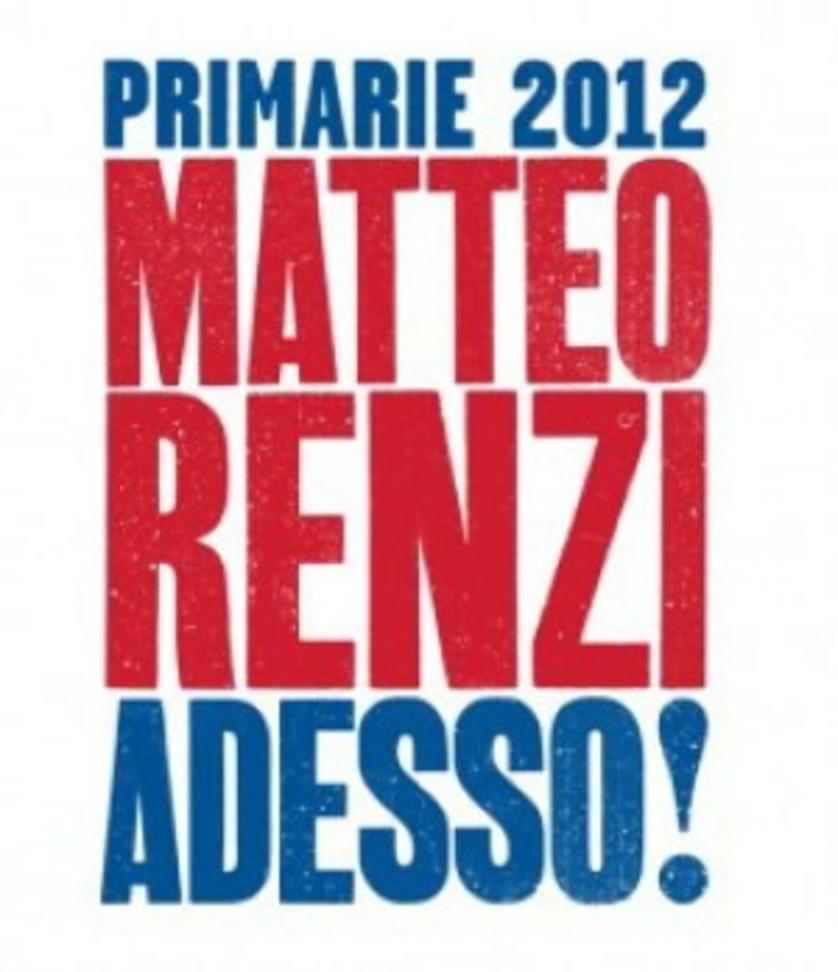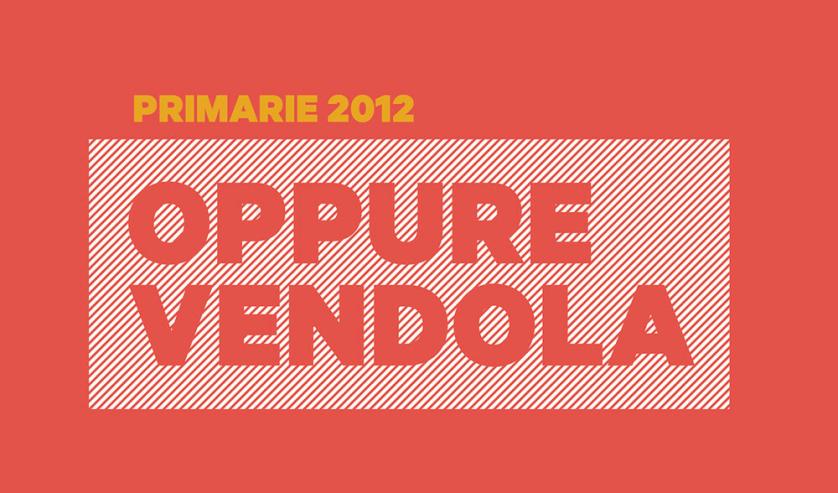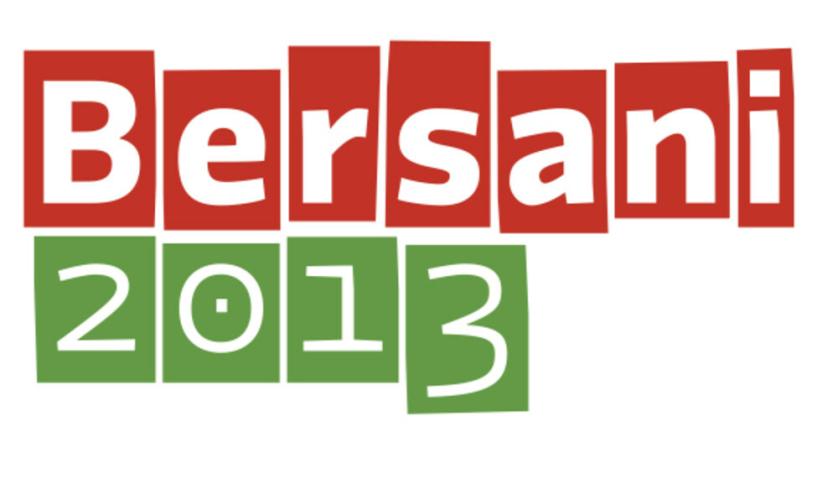
La tipografia delle primarie: JFRenzi, PierLouis e Vendolik
Un anno e mezzo fa, in questa rubrica, scrissi di tipografia e comunicazione politica: Milano ne fu per qualche settimana un pessimo ma interessante esempio.
Poi tutto si appiattì. Il rigore montiano avvolse anche la comunicazione visiva. Per mesi abbiamo visto solamente le identità visive di forum economici in cui la facevano da padrone Monti, Draghi, Baskerville, Caslon e Garamond e Bodoni. Un’Europa finalmente unita.
Ma ora basta. Finalmente ci stiamo avvicinando alle elezioni e le schermaglie tipografiche sono iniziate. Restando Berlusconi ancora al margine della competizione, ci dobbiamo accontentare delle scaramucce a suon di “bastoni” tra i principali candidati alle primarie del Partito Democratico. Ma questa volta si sono impegnati veramente e ci stanno regalando grandi soddisfazioni.
In molti hanno accusato Matteo Renzi di essere “Obamified”. Non sanno invece che il ragazzino terribile, il nuovo che avanza, non è altro che stile vintage. Altro che Obama: le maniche di camicia arrotolate, la riga in parte e il piccolo ciuffetto che sta crescendo completano il kit del giovane democratico che ci salverà. I caratteri che compongono il suo nome e la parola d’ordine “Adesso!” sono condensati e molto grossi. Derivano, nel disegno, da quelli di legno che si usavano per comporre i manifesti due secoli fa, di ispirazione nordamericana. Un po’ come l’Impact berlusconian-leghista di cui scrissi su questo sito. Ma soprattutto composti in quel blu e rosso da convention americana, non possono non ricordarci le campagne democratiche degli anni sessanta. Soprattutto quella di JFK.
Perciò, “Fuori dal Vietnam, ADESSO! Tutti alle Cayman!”.
Il problema (di questi tempi lo è) potrebbe essere ricordare invece la campagna molto simile di Richard (Dick) Nixon. Ma soprattutto se l’avversario per lui sarà Berlusconi (notizia di oggi ci rassicura di no) potrà riciclare uno dei più famosi slogan non ufficiali di quella campagna: “THEY CAN’T LICK OUR DICK”. Il carattere e i colori sono quelli, la sfrontatezza pure.
Mentre il ragazzo vintage percorre l’Italia stipato nel camper assieme a quelle letterone giganti che si porta dietro sui palcoscenici (quando i contenuti sono light meglio delle lettere bold...), il vero innovatore tipografico è invece il rottamando Bersani.
La sua campagna è molto basata sulla elaborazione visiva della parola. Non solo. Ha addirittura un font ad hoc che viene poi modificato per interpretare le parole chiave del programma. Raro ed evoluto caso di comunicazione politica.
Per dire la verità il carattere è stato presentato come disegnato per il PD. Non so se il segretario se ne sia appropriato considerando che quel che si fa per il Partito gli appartenga. Forse PierLouis si è sentito un po’ come Louis XIV che si fece disegnare il carattere Romain du Roi usato per le pubblicazioni che lo celebravano. Rimane il fatto che è un passaggio notevole per la cultura grafica italiana quello di un partito politico che si fa disegnare un carattere. Il problema semmai è che un carattere da solo ha un relativo potere, che può essere vanificato da un suo pessimo uso. In fondo Obama usa da sempre il Gotham, che è estremamente diffuso non solo negli Usa. Nel caso Bersani 2013, i calembour tipografici eseguiti sono raramente riusciti e il logotipo frantumato (rottamato, forse) ha predecessori più nobili nei collage fatti per i Sex Pistols da Jamie Reid.
Rimane il terzo incomodo, l’alternativo, l’estremista. Mi sarei aspettato un carattere di default, democratico, a cui tutti possano accedere, magari open source. E invece il piacere del bello l’ha probabilmente spinto a farsi disegnare una vera e propria identità visiva per la campagna elettorale. Il carattere usato è una versione contemporanea di alfabeti tedeschi disegnati negli anni venti, quelli poi messi al bando dal regime nazista, nella versione più grossa, consistente, solida.
Il carattere è accoppiato al ritratto-caricatura di Vendola disegnato con un tratto in bianco e nero che marca attaccatura dei capelli e sopracciglia alla maniera di Diabolik. Il tutto, messo su fondi colorati, è prossimo a diverse campagne del PCI degli anni novanta, e più che innovativo appare fuori luogo. Non potremo farci governare per sempre da uno in loden, ma nemmeno da un fumetto.
Questo il panorama tipografico delle primarie del Centrosinistra nel 2012. Passi in avanti sono stati fatti. La tipografia ha dunque un suo ruolo forte e prevalente. E questo ci fa credere che la parola possa comunicare finalmente più del cerone e del cielo azzurro.